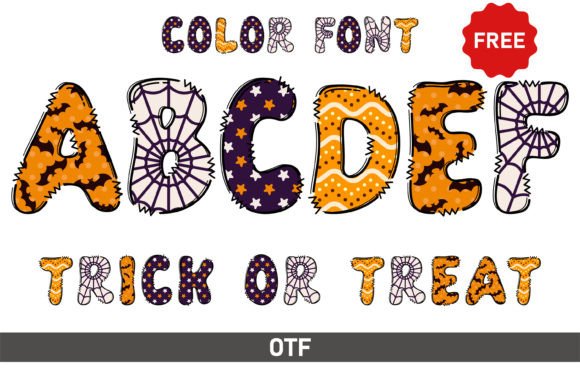
Trick or Treat
Trick or Treat – Review Completa
Se você está procurando uma fonte que traga diversão, criatividade e um toque artístico aos seus projetos, Trick or Treat pode ser a escolha perfeita. Esta tipografia foi desenvolvida especialmente para designs que precisam transmitir um clima lúdico, como livros infantis, cartazes, convites e cartões comemorativos. A seguir, apresentamos uma análise detalhada de suas principais características, compatibilidade e dicas de uso.
- Estilo lúdico e artístico: As formas arredondadas e as linhas suaves criam um visual encantador, ideal para atrair a atenção de crianças e adultos que buscam algo divertido.
- Legibilidade: Apesar do design criativo, a fonte mantém alta legibilidade, o que a torna excelente para textos curtos em capas de livros, banners e convites.
- Versatilidade de cores: Disponível em versão preta (compatível com máquinas de corte) e versão colorida (compatível com softwares como Photoshop, Illustrator, Silhouette e Inkscape).
Aplicações Ideais
- Livros infantis: tipografia divertida que estimula a leitura.
- Cartões de aniversário e convites de festas temáticas.
- Posters e banners para eventos escolares ou festas de Halloween.
- Produtos personalizados em máquinas de corte, como adesivos e decorações de festas.
Prós e Contras
- Prós: Design encantador, alta legibilidade, duas versões (preta e colorida) que atendem a diferentes necessidades de produção.
- Contras: A versão colorida não funciona em máquinas de corte Cricut, exigindo a utilização de softwares específicos.
Trick or Treat se destaca como uma fonte versátil e visualmente atraente, ideal para projetos que buscam um toque de magia e alegria. Se o seu trabalho envolve impressão digital ou design vetorial, a versão colorida oferece opções criativas ilimitadas. Já para quem trabalha com corte de vinil ou projetos físicos, a versão preta garante compatibilidade total com Cricut e outras máquinas de corte.